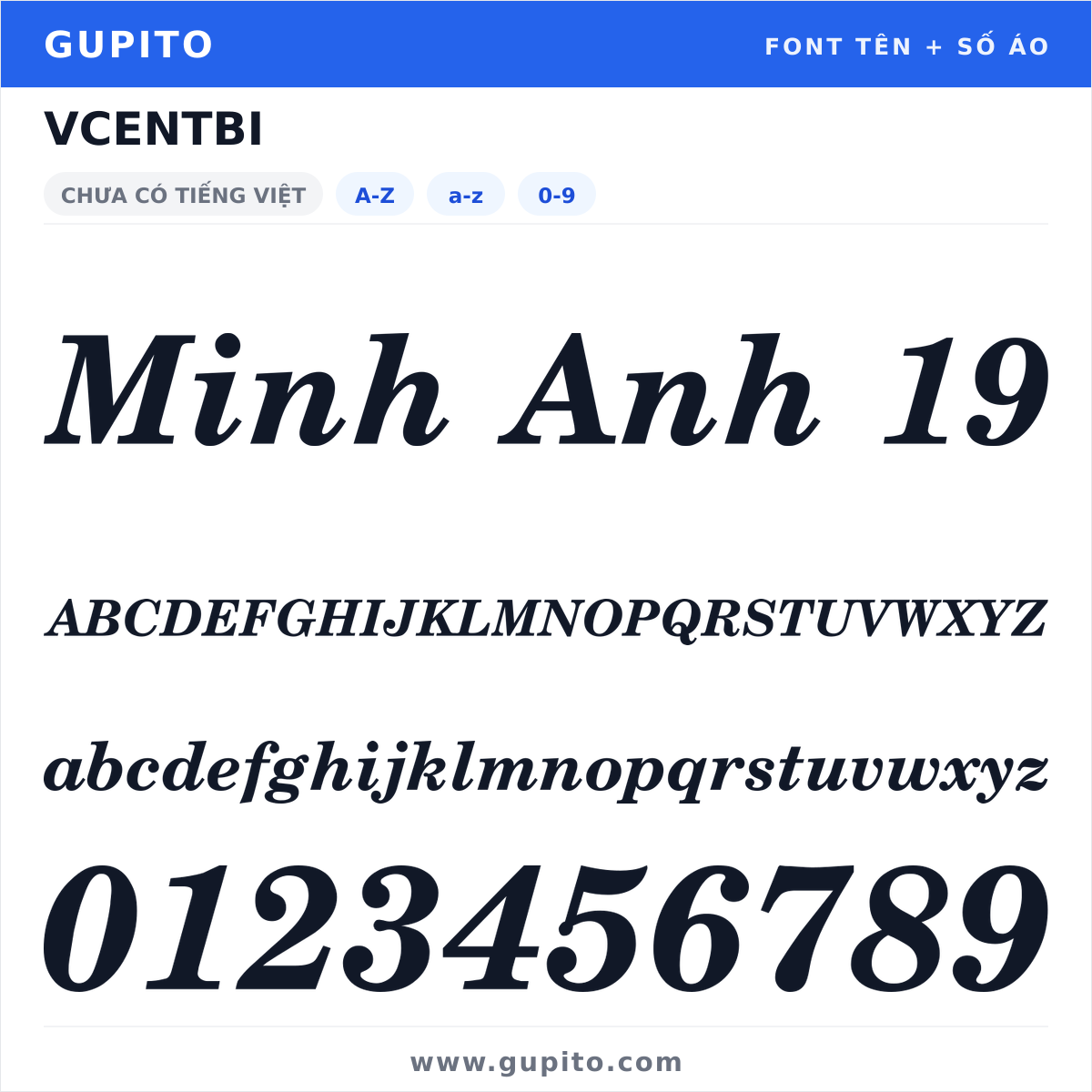
VNI-Centur-Bold-Italic
VNI-Centur-Bold-Italic · Font VCENTBI in tên áo bóng đá, số áo thể thao · chữ nghiêng đậm
Font VCENTBI với nét chữ đậm, nghiêng, chân chữ có chân, phù hợp in tên áo bóng đá, số áo, áo lớp, quà tặng. Bộ chữ VNI-Centur-Bold-Italic dùng để in chuyển nhiệt lên áo đấu, áo lớp, áo nhóm và đồ thể thao theo yêu cầu. Kiểu dáng: chữ nghiêng đậm. Font dùng cho chữ không dấu và số áo. Có đủ bộ chữ số để in số áo. Từ khoá liên quan: font vcentbi, font in ten ao, font in so ao, font ao bong da, font the thao, font chu nghieng, font chu dam, font in chuyen nhiet.